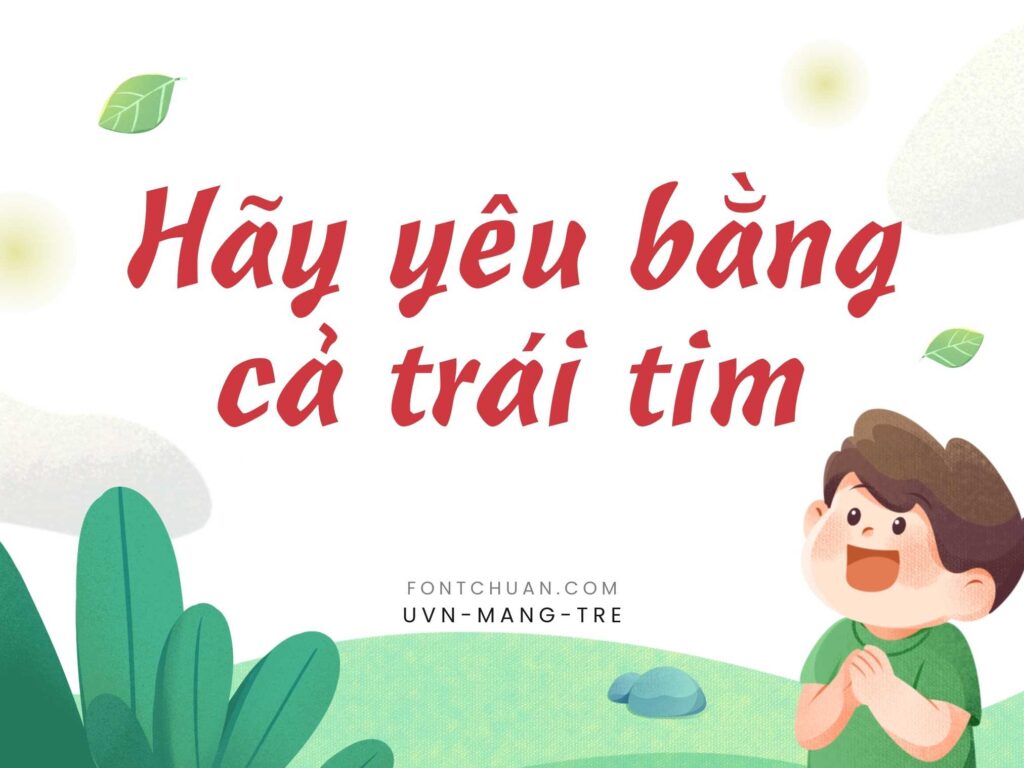
Font UVN Mang Tre Việt Hóa
UVN Măng Tre là một phông chữ thư pháp mang phong cách nghệ thuật viết tay truyền thống. Được thiết kế với các nét bút lông mềm mại và uyển chuyển, phông chữ này tạo nên sự thanh thoát và tinh tế cho các tác phẩm thiết kế. UVN Măng Tre hỗ trợ đầy đủ các ký tự tiếng Việt, giúp người dùng dễ dàng sử dụng trong các dự án sáng tạo liên quan đến văn hóa Việt Nam.
Với thiết kế độc đáo và nghệ thuật, UVN Măng Tre phù hợp cho các ứng dụng như thiệp mời, tiêu đề sách, thiết kế logo và các ấn phẩm nghệ thuật. Trong lĩnh vực sự kiện, phông chữ này có thể được sử dụng trong các dịp như lễ hội, lễ cưới và các sự kiện văn hóa. Bên cạnh đó, nhờ tính thanh thoát và dễ đọc, UVN Măng Tre còn là một Font chữ giáo dục lý tưởng, phù hợp để thiết kế các tài liệu học tập, sách giáo khoa, bài giảng hay các ấn phẩm giáo dục trực tuyến, giúp truyền đạt nội dung một cách sinh động và dễ tiếp nhận.